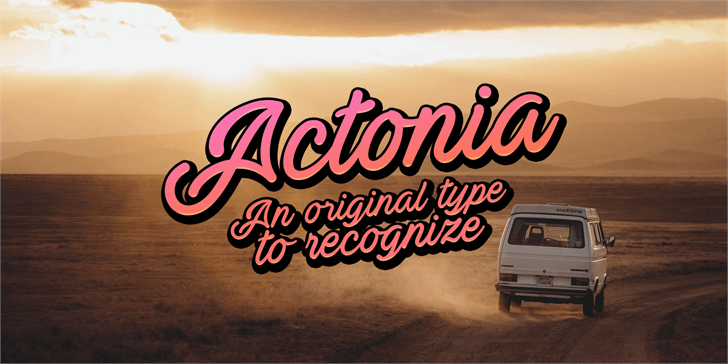
Actonia Font
A fonte ‘Actonia Font’ é uma mão-dura criada pelo designer Hamilton que combina um estilo minimalista com a suavidade do escrita à mão. Ela é perfeita para personalizar qualquer projeto de design gráfico, especialmente em editoriais e cartazes, oferecendo texturas naturais e uma aparência elegante. Se você busca uma fonte que traz ao seu trabalho um toque autêntico sem comprometer a clareza, ‘Actonia Font’ é perfeita para você. Visite o site do designer para comprar sua própria licença comercial. Combinada com os designs da Hamilton, esta font oferece uma experiência visual única que certamente deixará seu projeto brilhar ainda mais.